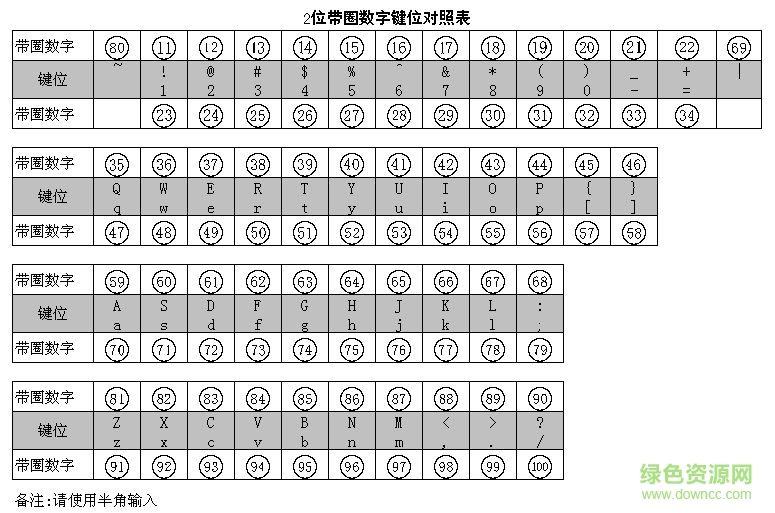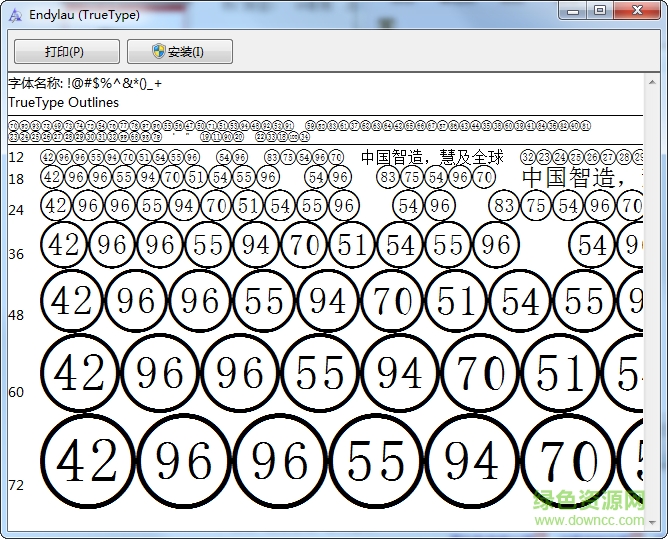
一、制作緣由
在日常的工作當中,有些朋友需要在MS WORD或者excel等辦公軟件中輸入帶圈數(shù)字,我們通常是通過OFFICE自帶的插入帶圈字符的辦法達到目的。但是通過此方法插入的帶圈字符尤其是帶圈兩位數(shù)字,在改變其字號以后,里面的數(shù)字會溢出圈外,如果輸入的帶圈字符教多,調(diào)整起來非常麻煩。
所以,受網(wǎng)友所托,我制作了此款字體文件Endylau.ttf。
二、字體介紹:
Endylau.ttf文件是數(shù)字11到100的帶圈數(shù)字的字體文件。其安裝方法同其它字體一樣,最簡單的方法就是把Endylau.ttf文件復制到字體文件夾(控制面板——字體)中即可。使用方法也同其它字體一樣,此處就不在贅述。